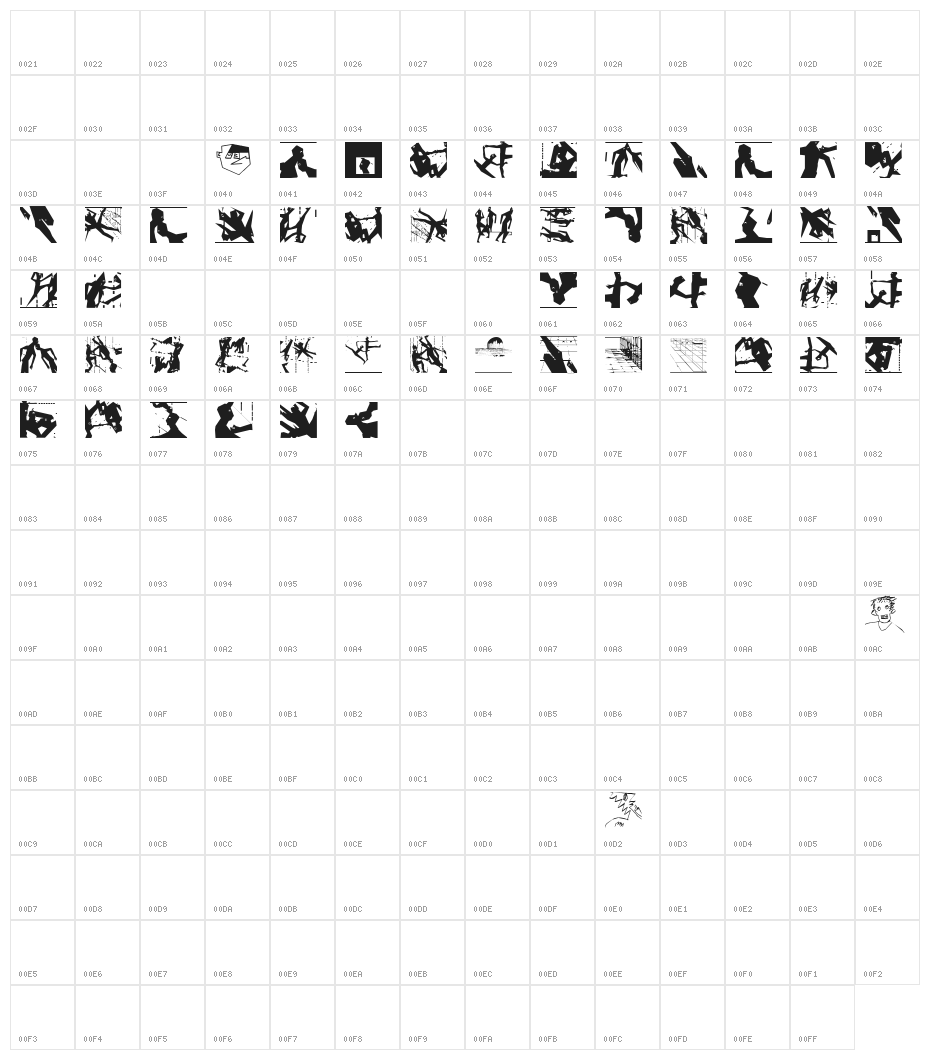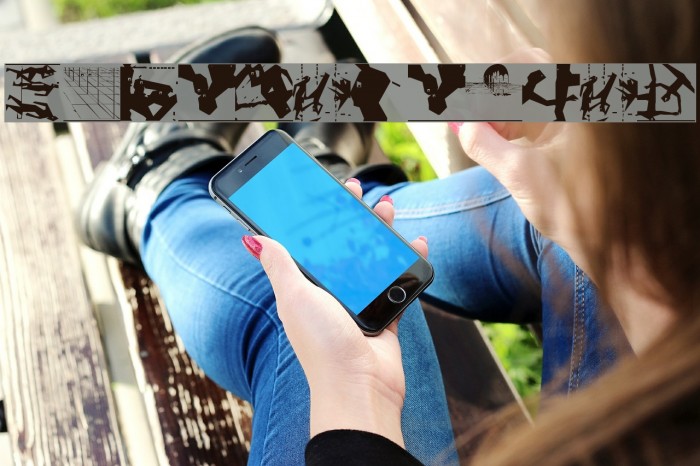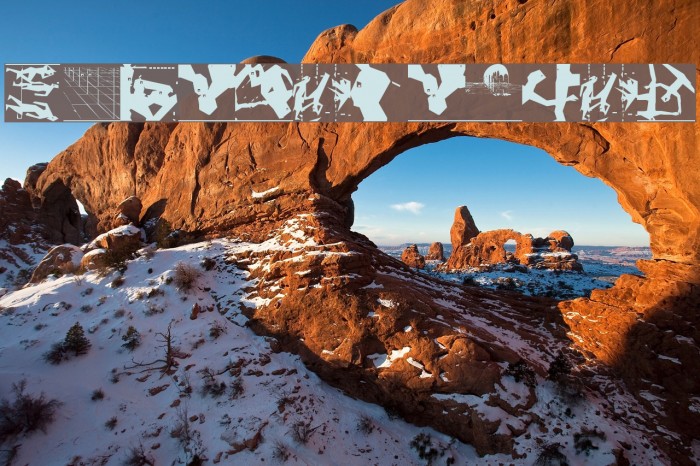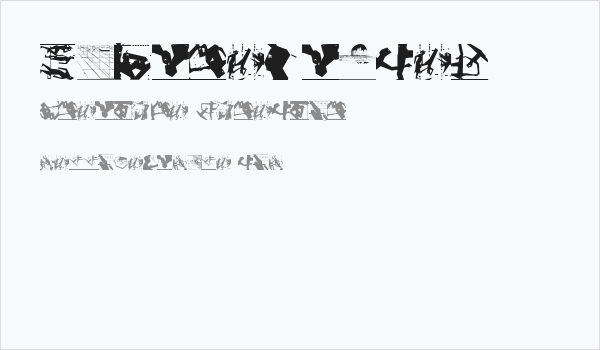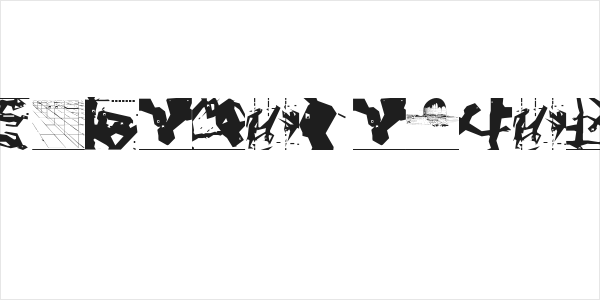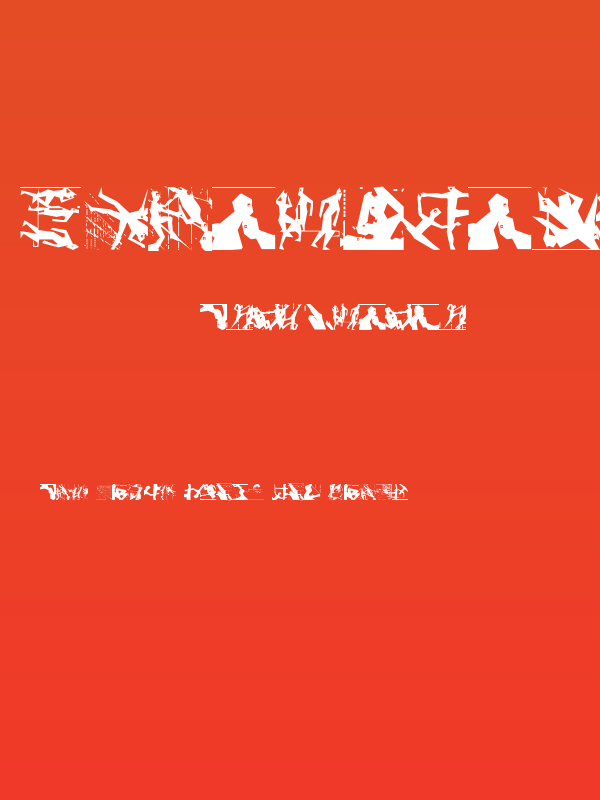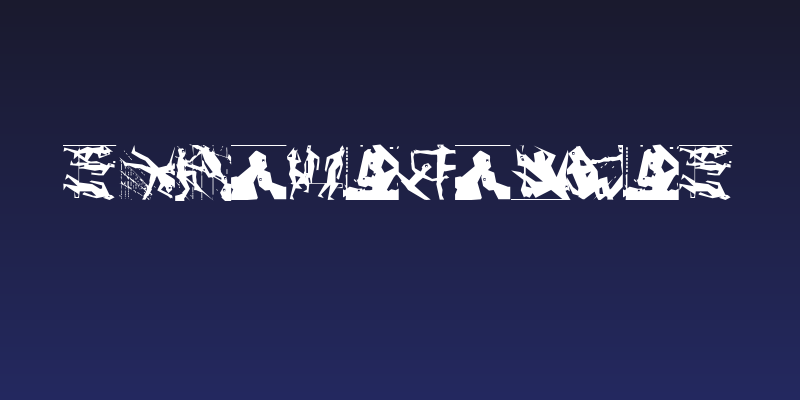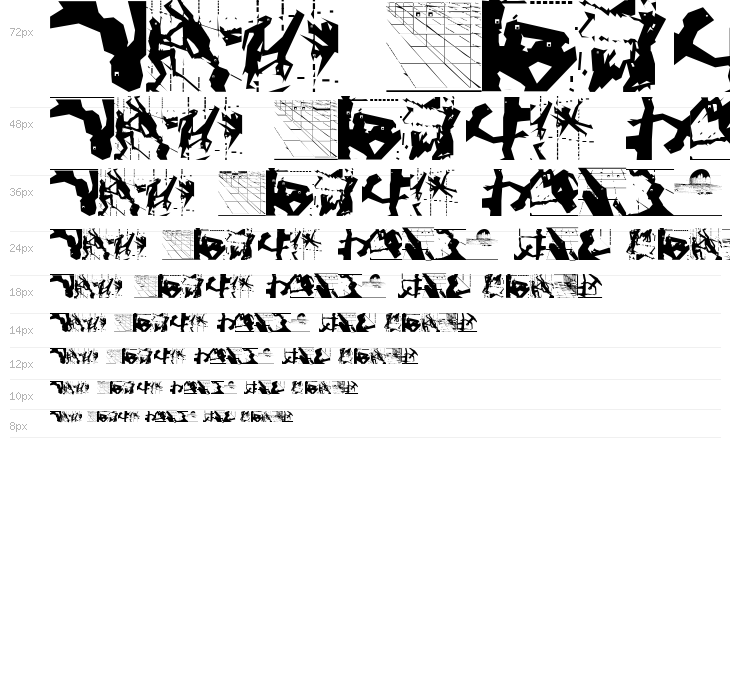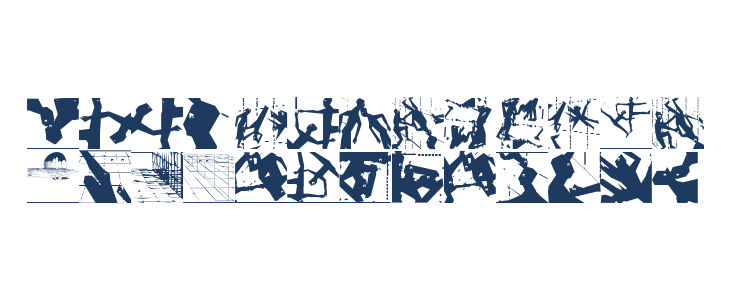
Squaredances Font
SQUAREDANCES Groß
SQUAREDANCES Kleinbuchstaben
SQUAREDANCES Anderer Schreiben
| Anwendungsfall | Logos, Headlines, Artistic projects |
| Vorgeschlagene Projekte | Ideal for creative projects such as posters, album covers, or event flyers where a bold, artistic statement is desired. |